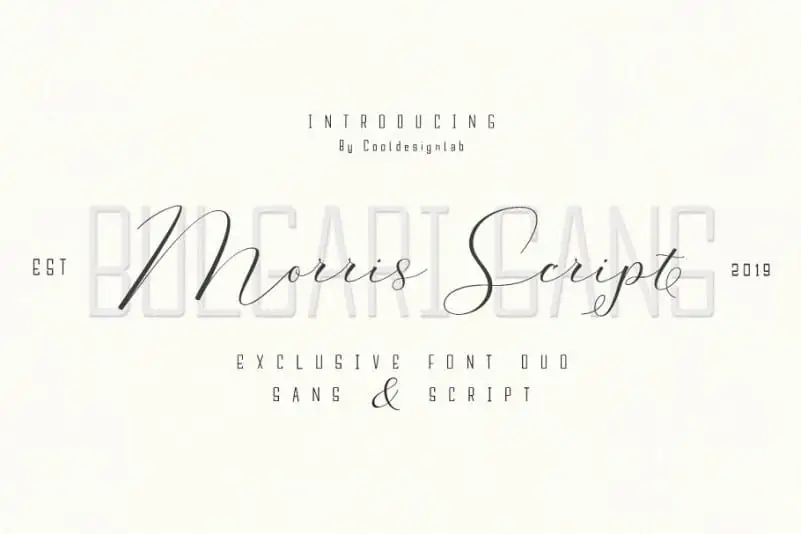
Agora você tem a opção perfeita para destacar seu trabalho nas principais ocasiões e projetos com uma fonte que combina elegância e naturalidade: Morris Script Font Duo. Esta fonte é baseada na escritura manual de caligrafia, oferecendo um estilo arredondado moderno e sofisticado. Seu traçado exuberante e fluido permite que você personalize seu trabalho com riqueza em detalhes sem comprometer o resultado elegante. Ideal para criar identidades visuais memoráveis, Morris Script Font Duo é a escolha perfeita para invocar um ar de elegância em cartões de visita, materiais de marca, convites e até mesmo postagens de propaganda. O conjunto extra da fonte sans-serif Bulgari Sans adiciona ainda mais versatilidade ao seu trabalho. Com suas linhas fluidas e caracteres chamativos, a Morris Script Font Duo se destaca para os profissionais que buscam criar um toque personalizado em seus projetos. Ideal tanto para iniciantes quanto para designers experientes, essa fonte é uma ótima escolha para qualquer projeto de design gráfico. Seja você uma designer digital ou impressa, a Morris Script Font Duo oferece a oportunidade de expressar sua marca com autenticidade e sofisticação. Seja em cartões de visita ou painéis publicitários, seu design estará imediatamente reconhecível como único, fazendo dele um recurso indispensável para qualquer projeto visual.